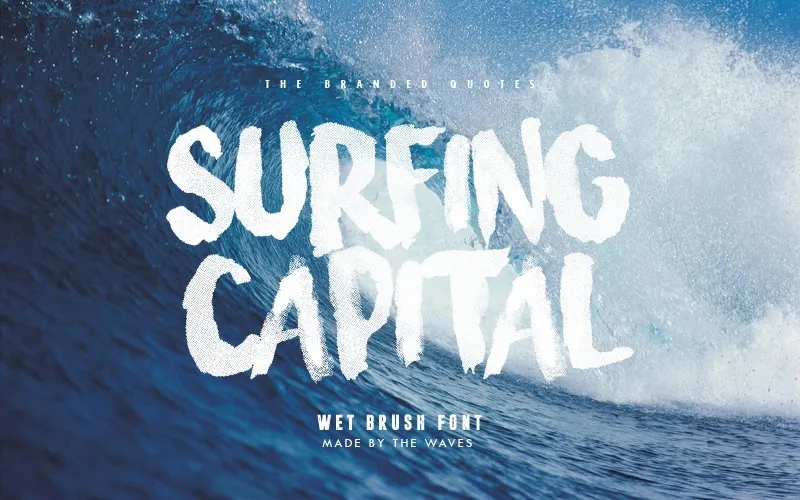
A Surfing Capital é uma fonte brush que traz a essência do surf para seu design, combinando movimento e liberdade na escrita. Ideal para criar mensagens pessoais ou artísticas de maneira única, esta fonte é perfeita para os amantes da cultura do mar. Para uso comercial, Hamilton solicitou apenas um simples passo: envie uma mensagem por email para . Em troca, você não só pode utilizar essa bela fonte em seu trabalho, mas também ajudar a difundir um pouco dessa experiência divertida e gratificante na sua própria comunidade. Um gesto tão fácil de fazer, que traz grandes benefícios à todas as partes envolvidas. Desde uma pequena economia para seus clientes até o prazer pessoal do designer, essa fonte é pura surpresa. Não hesite em adicionar seu sabor personalizado ao texto e faça a diferença. Agradeçamos sua visita e partilhemos esta maravilha de arte.